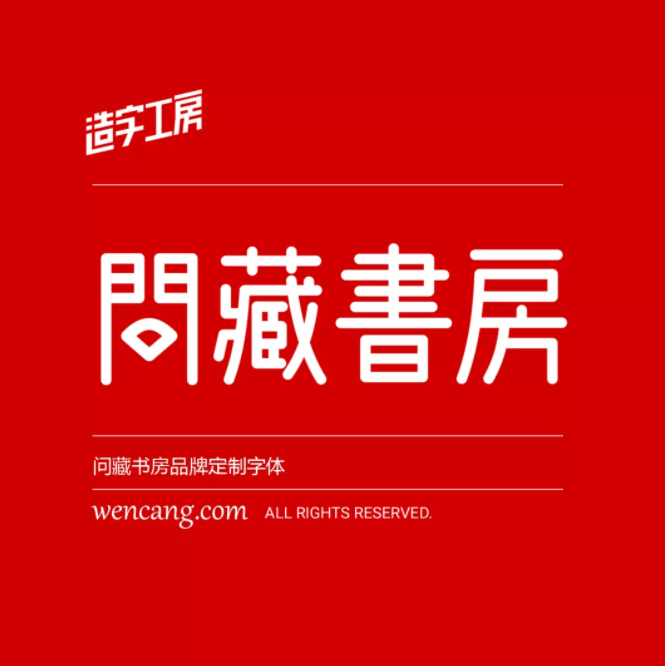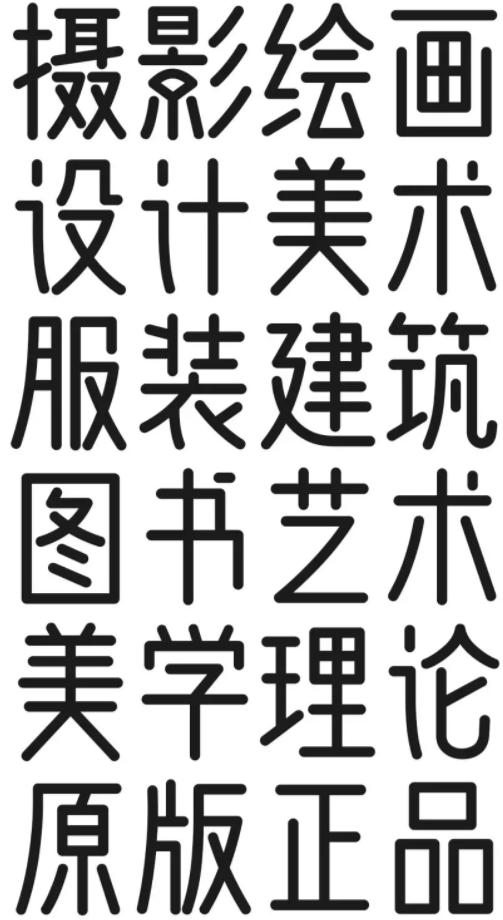
问藏书房品牌字体正式发布,免费可商用
问藏书房是造字工房创始人丁一将二十年余年收藏和学习的数千本设计、绘画、摄影、字体等艺术图书全部捐助于问藏书房而创建。意向通过问藏书房免费借阅给对设计与艺术、美学类相关知识有兴趣的同学。在各界朋友的帮助和造字工房创新资金全力支持下,投入数百万元,将艺术与美学类书籍的藏书量增至万余册,一并无偿借阅给热爱书籍、对审美有更高需求的朋友们,以实际行动为中国的审美教育贡献一份绵薄之力!
问藏书房字体的设计整体现代简约,中宫紧凑,视觉阅读极具层次感,字字俊秀且呈现古雅之风,设计团队以精心的设计赋予了汉字全新美感!字符编码采用中华人民共和国GB2312-80字符集标准,按需添加101个汉字。共收容字数6864CJK汉字,ASCII常用字符100个。